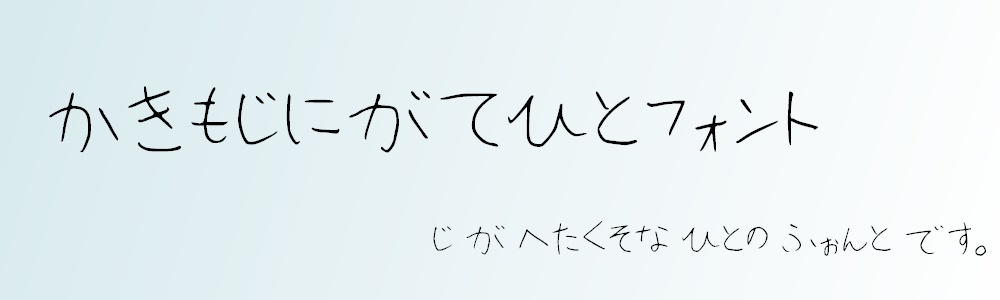
書き文字苦手人フォント
■ このフォントについて 「書き文字苦手人フォント」は、手書き文字をもとに作成したフォントです。 ■ 収録内容(無償版) ・Read me(収録文字詳細+Booth文章) ・フォントデータ 英字(大文字/小文字) 数字(0~9。アラビア数字のみ) 記号(27点) ・無償版の文字一覧PNG ・有償版の文字一覧PNG ※動作確認用にお使いください。 ■ 収録内容 (有償版) ・Read me(収録文字詳細+Booth文章) ・フォントデータ ひらがな カタカナ 英字(大文字/小文字) 数字(0~9。アラビア数字のみ) 記号(40点) ・有償版の文字一覧PNG ※漢字は一切入っておりません!! ■ 利用について ・本フォントは個人利用の範囲でご使用いただけます。 ・商用利用(有償配布物・業務利用・収益化を伴う使用など)は禁止します。 ・再配布(加工したもの/未加工のもの問わず)、フォントデータのそのもの販売は禁止します。 ・著作権は放棄しておりません。自作発言はお控えください。 ・判断に迷う場合は、ご使用お控えください。 ■ 注意事項 ・手書き文字を元にしているため、文字の形やサイズにばらつきがあります。 ・本フォントの使用によって生じたトラブル等について、制作者は責任を負いません。 ・有償版のDL前に、無償版でのテストを何卒よろしくお願いします! ・Win11では動作確認をしていますが、Macではできていないので、本当にチェックしてからの利用をお願いします。 ■ 制作者 ことの ※フォントデータの著者名は「kotonot」になっています。